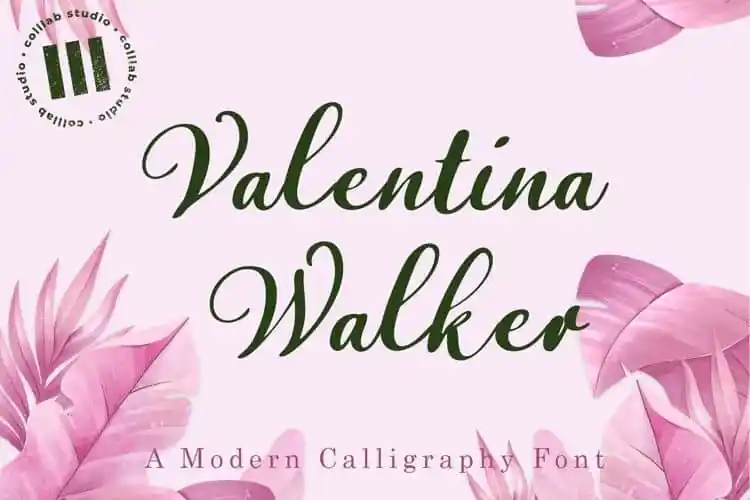
Valentina Walker Script Font – Fonte Grátis
Valentina Walker Script Font
A Valentina Walker Script Font é uma elegante escolha para aqueles que buscam arredondar as bordas do digital com um toque sofisticado e contemporâneo. Criada pelo talentoso designer Colllab Studio, a fonte adquirem o ar de um autêntico caderno de notas manuscrito, uma mistura harmônica de elegância e fluida fluidez que se encaixa perfeitamente em qualquer projeto criativo. Seus caracteres são bem balanceados e detalhadamente elaborados, tornando-a uma fonte ideal para estilos variados desde cartazes até designs digitais mais refinados. Com apenas uma pequena introdução de Valentina Walker Script Font a seu trabalho, você notará o quanto ela dá vida ao conceito criativo. Não é à toa que esta font se destaca entre tantas outras, sendo uma opção perfeita para quem busca um estilo sofisticado e moderno em sua próxima projeto visual.